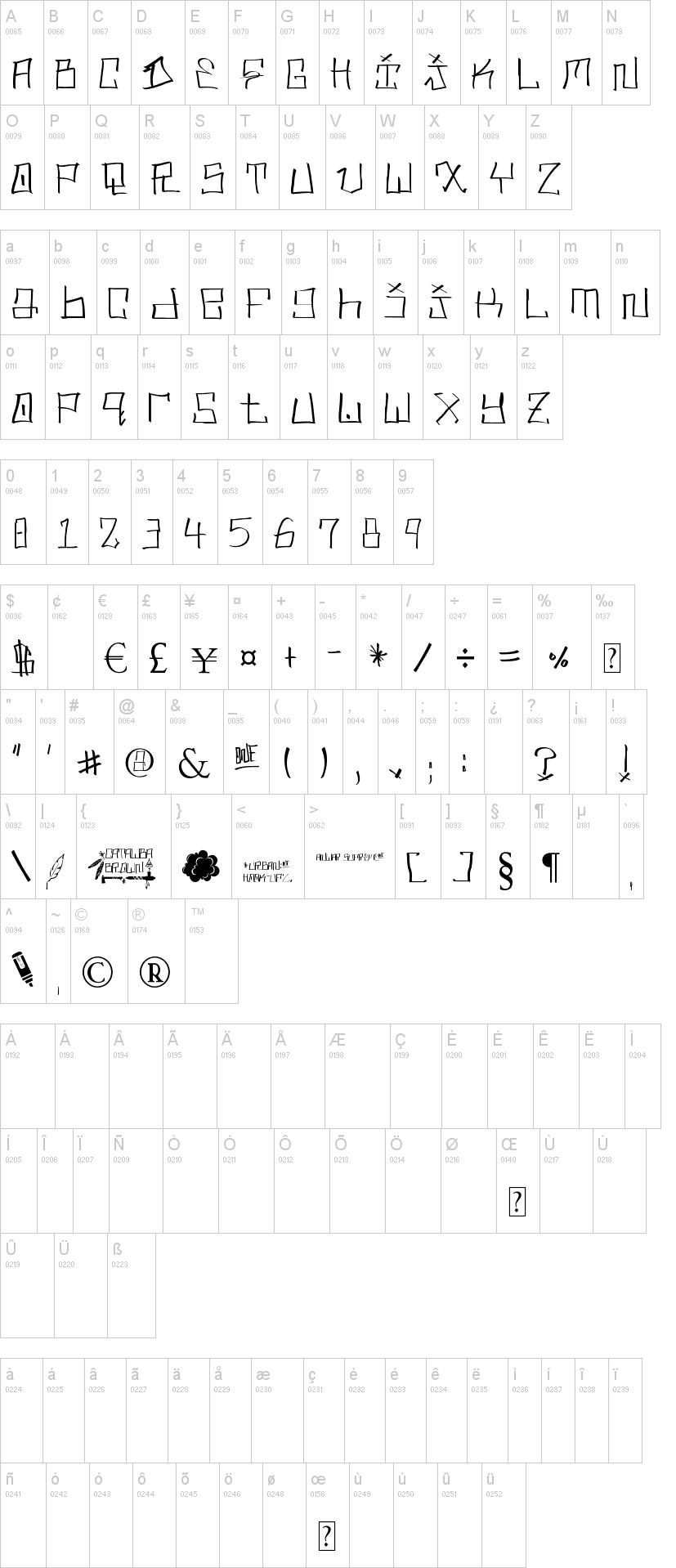
Mr. Brown 是一种非常流行的手写风格字体。它的设计风格非常干净、自然、轻松,可以营造出一种友好、亲切的感觉。它的笔画有些不规则,有些毛糙,但这正是它的设计特色。 Mr. Brown 字体适用于各种设计领域,如海报、标志、广告、包装、印刷品等。它的字母形状非常清晰,易于阅读,适合用于各种大小的文本。另外,Mr. Brown 字体还提供了多种版本,如正常、斜体、粗体等,可以根据不同的需求进行选择。内容介绍
Mr. Brown是一款非常不错的手写艺术字体,具有很好的视觉感,适合于文化类的宣传设计、商业类品牌的广告和产品包装设计以及个性化文字排版等较多场景。